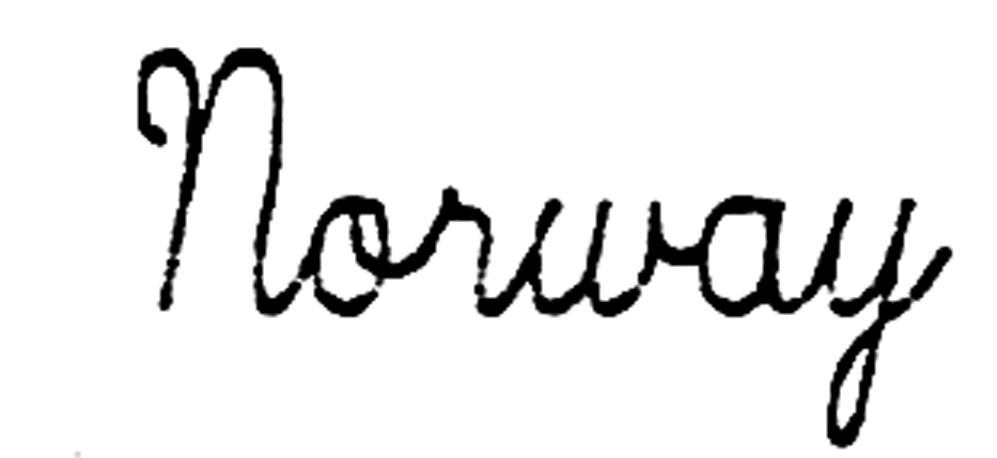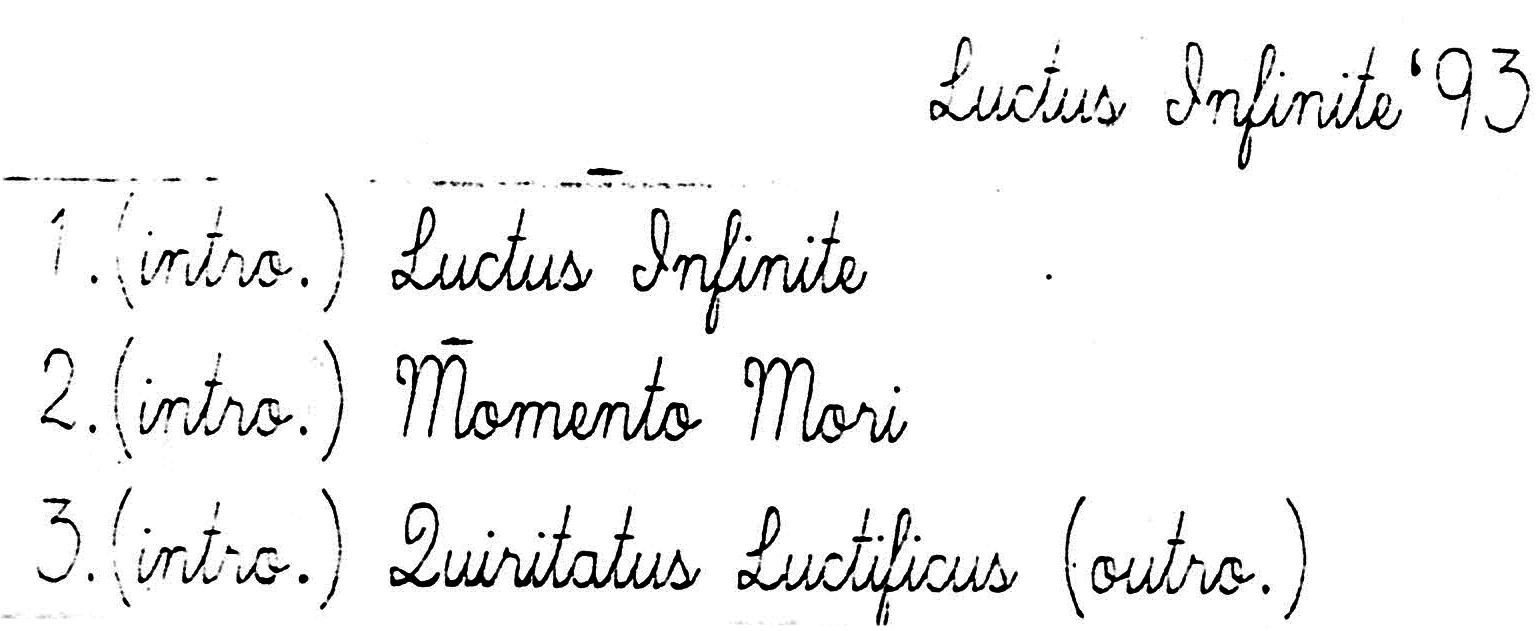
Schulschreibschrift gesucht (Luctus infinite, Cruciamentum)
für ein offizielles Vinyl-Release suche ich eine Schreibschrift. Sie wurde 1992 für ein Democover verwendet. Ich finde nur ähnliche Fonts, es sollte aber genau dem Original entsprechen. Danke für eure Hilfe.
Am besten die Person kontaktieren, die das handschriftlich geschrieben hat und um Mitarbeit bitten. ;-)
Hmm .. OK, Du bist der Experte. Dann sind die kleinen Unterschiede mit der schlechten Qualität zu erklären.